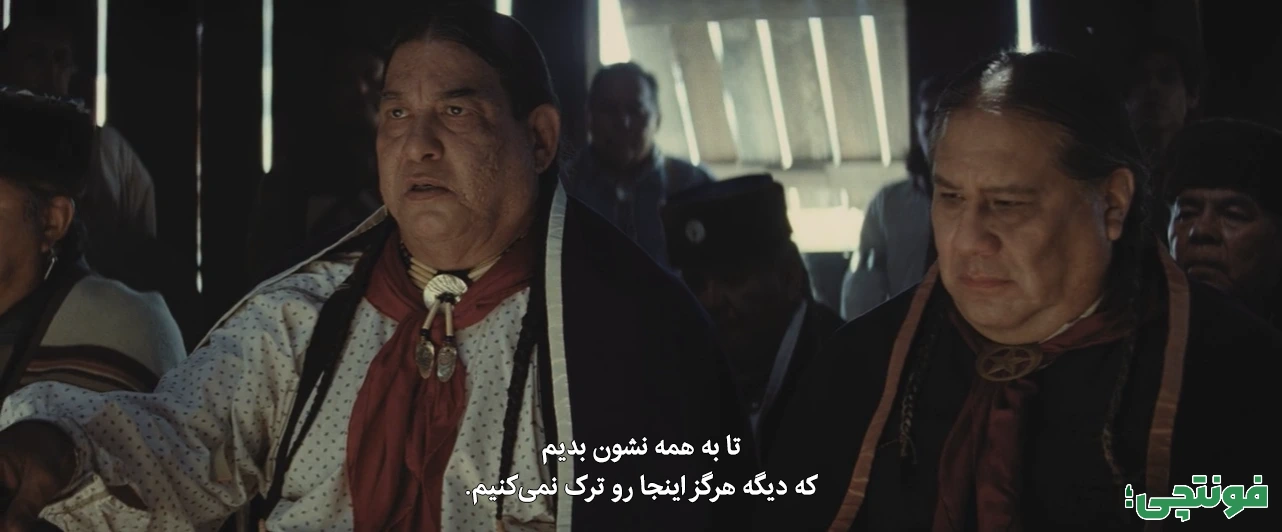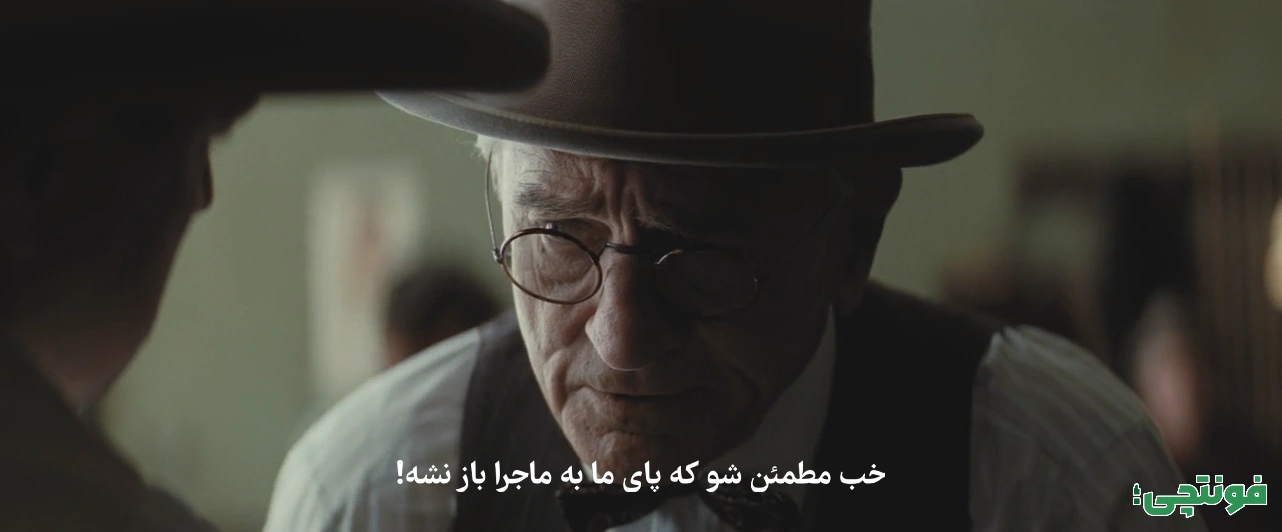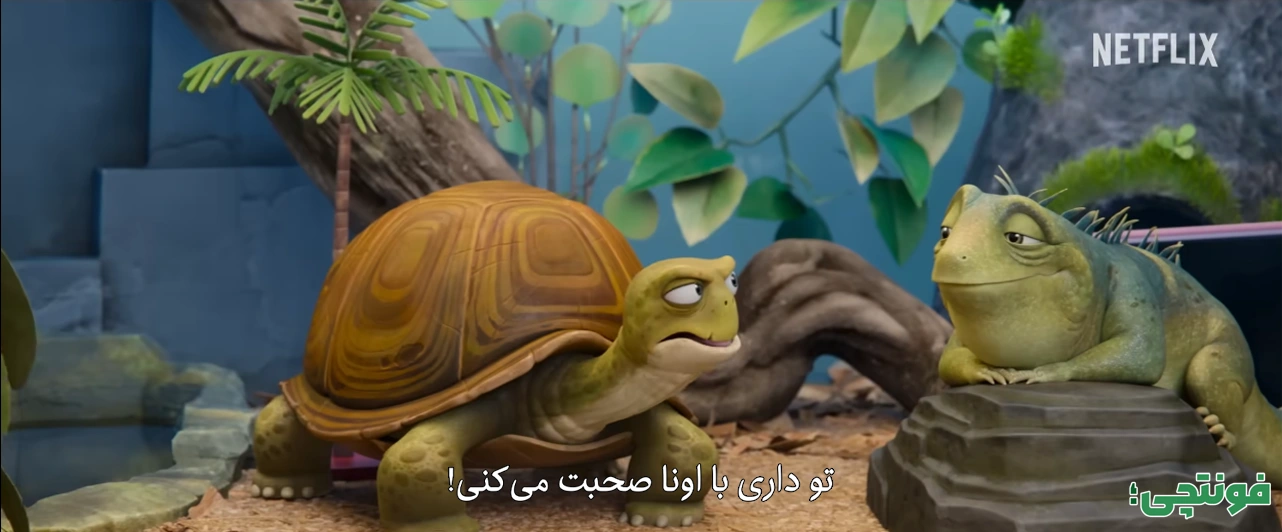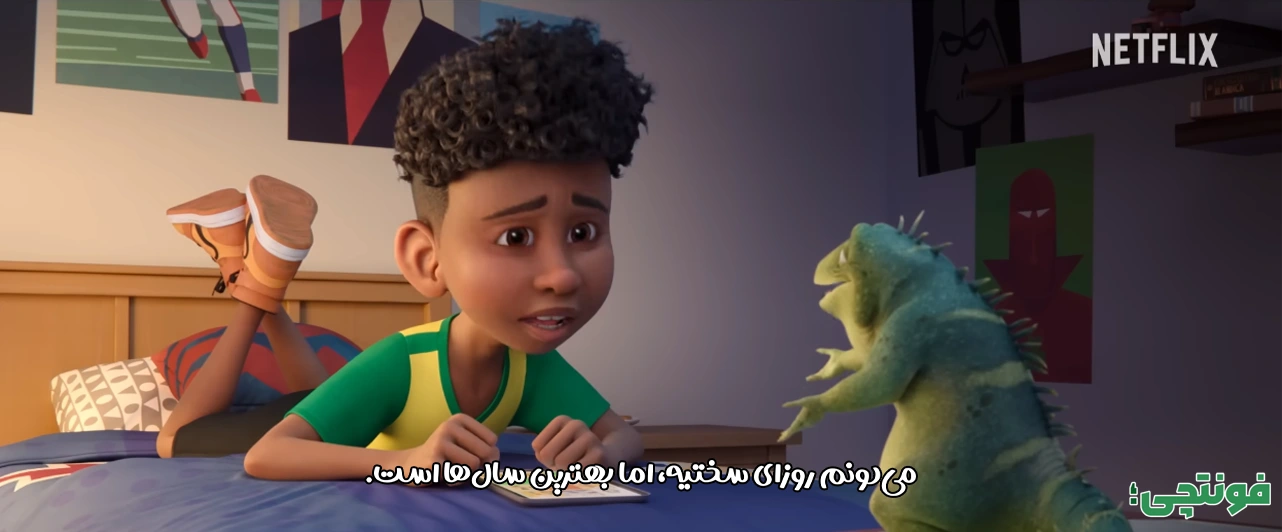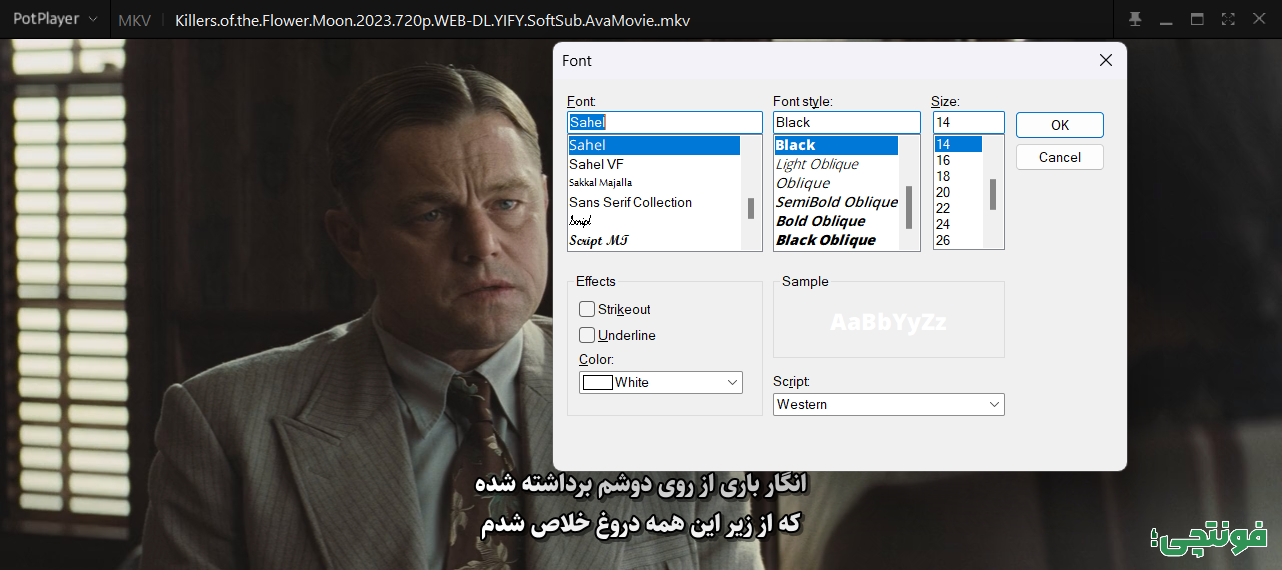
بهترین فونت زیرنویس فیلم و سریال [10+ فونت محبوب]
احتمال میدهم شما هم جزو معدود افرادی هستید که دیدن فیلم و سریال با زبان اصلی را ترجیح میدهند. خصوصا در شرایطی که شاهد تغییر کلی خط داستانی برخی فیلمهای دوبله شده هستیم. مسئله مهمی که شاید خیلیها به آن توجه نکنند زیرنویس فیلم است. انتخاب بهترین فونت زیرنویس فیلم و سریال یکی از راههایی است که میتواند به افزایش لذت دیدن فیلمهای دوبله نشده کمک کند.
وقتی از خیلی افراد علاقهمند به فیلمهای دوبله شده میپرسم چرا فیلم با زبان اصلی نمیبینید؟ پاسخ آنها عموما این است که احساس راحتی ندارند از اینکه صحنه را دنبال کنند یا اینکه به دنبال کلمات زیرنویس باشند. در حالی که اگر روی انتخاب فونت مناسب زیرنویس، تغییر اندازه و حتی جایگاه نمایش آن کمی وقت بگذارند این مشکلات نیز برایشان رفع خواهد شد.
در ادامه این نوشته از وبلاگ فونتچی به بررسی چندتا از بهترین فونت زیرنویس فارسی برای فیلم، سریال و انیمیشن خواهم پرداخت که با استفاده از آنها میتوانید تجربه لذتبخشی در دیدن فیلم، که یکی از محبوبترین سرگرمیهای دنیای امروز است داشته باشید.
بهترین فونت زیرنویس فیلم و سریال
پیش از معرفی فونتهای مناسب زیرنویس لازم است که به چند نکته توجه داشته باشید:
- فونتهای معرفی شده در این نوشته بر اساس ساختار آنها از نظر طراحی و ظاهر قلم دستهبندی شدهاند.
- مسلما این لیست محدود به این موارد نبوده و دهها فونت مناسب دیگر هم وجود دارد.
- مهمتر از همه اینکه، در انتخاب فونت برای زیرنویس فیلم، راحتی بیننده از هر لحاظ اهمیت دارد. پس اگر با فونتهای معرفی شده به هر دلیل احساس راحتی برقرار نمیکنید، بهتر است که سایر فونتها را تست کنید تا چیزی که واقعا با شرایط شما ایدهآل است را انتخاب کنید.
خطر اسپویل: پیش از اینکه ادامه این مطلب را مطالعه کنید، تصاویر این نوشته همراه با فونت زیرنویس فیلم Killers of the Flower Moon 2023 و انیمیشن LEO 2023 تهیه شده است.
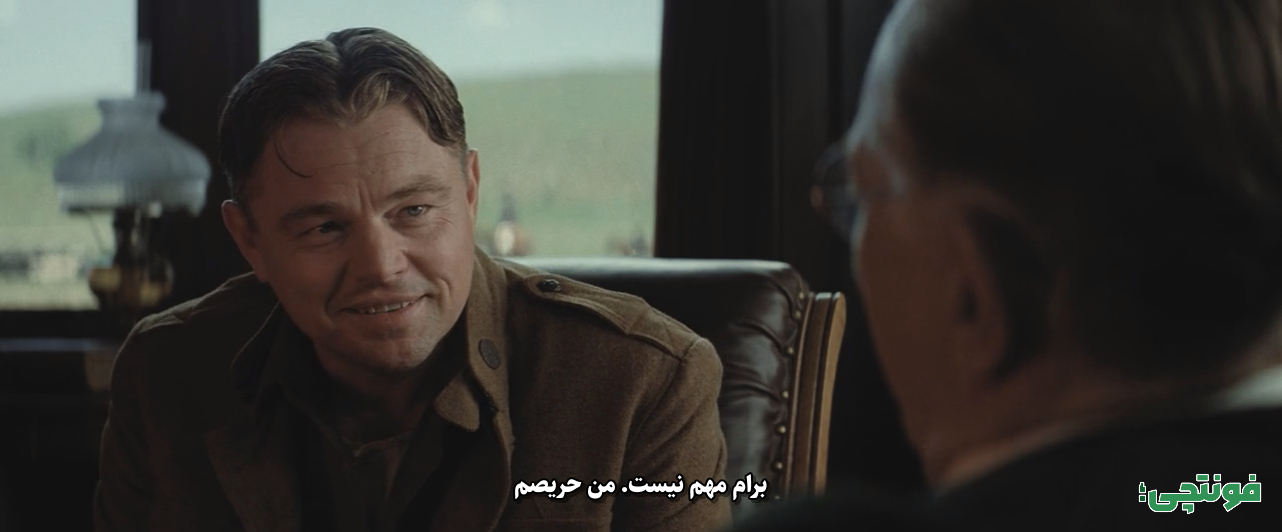
فونت ساحل
فونت ساحل از ساختههای مرحوم صابر راستی کردار است که شخصا بیشترین راحتی را در استفاده از این قلم برای زیرنویس فیلم دارم. مخصوصا در نسخههای ضخیمتر همچون Black که برای نمایشگرهای بزرگتر از ۲۰ اینچ واقعا کاربردی است.
طراحی حروف و کلمات در این فونت بهترین میزان خوانایی را دارد. با اینکه در نگاه اول بیشتر برای عناوین مناسب به نظر میرسد؛ اما در ساختار متن بهخوبی قابل خواندن است. خصوصا برای زیرنویس که سرعت خواندن آن به منظور از دست ندادن صحنهها و همچنین زاویه دید بهتر خود را نشان خواهد داد.
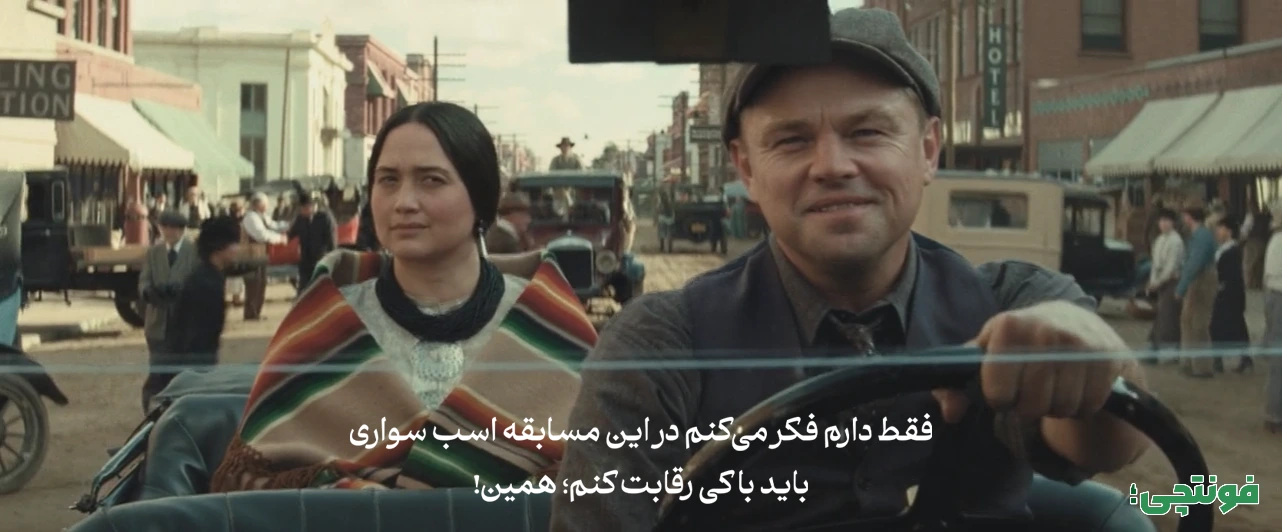
فونت گرامافون برای فیلم تاریخی
بسیاری از افراد به فیلمهای تاریخی علاقه دارند. خودم که شخصا در بین فیلمهای تاریخی به آنهایی که در گروه بیوگرافی بوده و عمدتا بر اساس واقعیت نیز ساخته شده باشند علاقه جدی داشته و دنبال میکنم. پس چه بهتر از قلمی استفاده کنیم که همان حس و حال تاریخی را به بیننده انتقال دهد.
گرامافون یک فونت مناسب زیرنویس فیلم تاریخی است که خود نیز همین سبک تاریخی و نوستالژی گونه را در طراحی حروف دارد. این فونت مجهز به طره هایی در برخی حروف «الف، ک، گ، ل، ط، ظ» است که وجود همین طرهها میتواند در نگاه غیرمستقیم به زیرنویس، خوانش متن و دنبال کردن آن را تا حدی بهبود دهد.
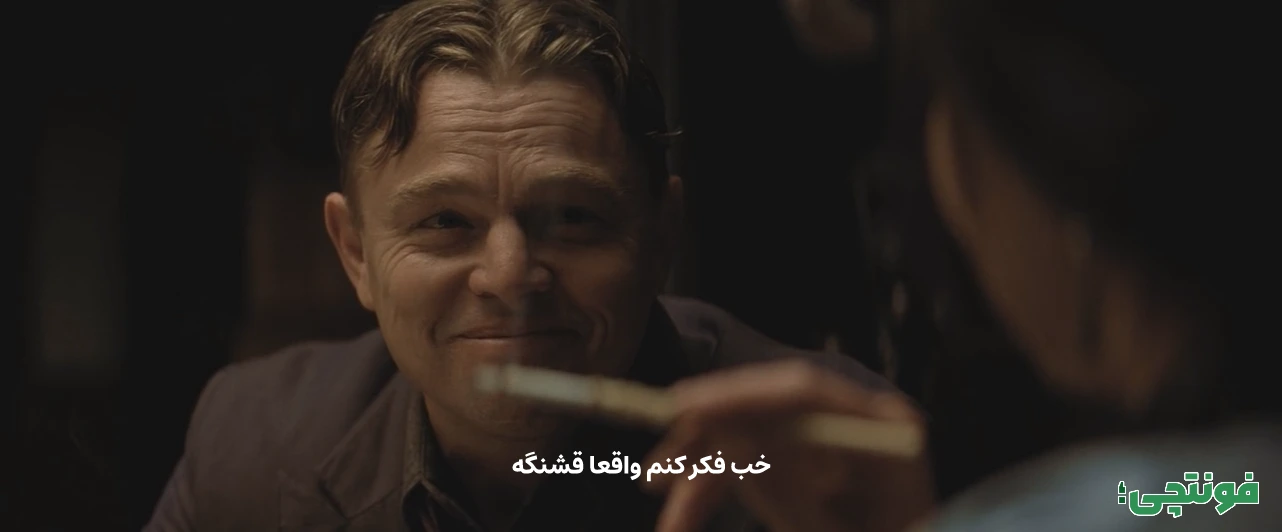
فونت استعداد
اگر به دنبال بهترین فونت زیرنویس رایگان هستید، استعداد یکی دیگر از گزینههایی است که به سادگی نمیتوان از کنارش عبور کرد. این فونت که از نسخه وریبل و پشتیبانی از چند زبان مختلف طراحی شده است، سبک خاصی را در برخی حروف دارد.
در فونت استعداد گردی حروفی همچون «ی، ن، ل» و ساختار متفاوت برخی حروف دیگر که شاید در تضاد با ساختار کلی فونت بهنظر برسد، شکل خاصی را به کلمات خواهد داد که گویی کلمات با ایجاد تضادهایی دستهبندی شده تا سرعت خوانش متن را بالا ببرد.
ویژگی مثبت این فونت برای زیرنویس همین مسائل است. خصوصا اگر از نمایشگر بزرگ برای دیدن فیلم زیرنویس استفاده کنید، وزنهای Bold و احتمالا ضخیمتر Black میتواند سرعت خواندن متن را بالاتر برده و هماهنگسازی بین زیرنویس و دیدن صحنه ها را در حد بالایی حفظ نماید.
فونت ایران سنس X برای زیرنویس
از دیگر فونت های مناسب زیرنویس فارسی ایران سنس است که جزو بهترین فونت های فارسی برای وب سایت است. این قلم نیز از چندین وزن مختلف با امکانات متعدد همچون سبک نقطه گذاری پشتیبانی میکند که اگر مایل به استفاده از نقاط پیوسته باشید انتخاب خوبی خواهد بود.
جدای از همه ویژگیهای مثبت این فونت، خوانایی این قلم به شدت بالاست. به طوری که محدود به زیرنویس فیلم نبوده و در محیطهای مختلف میتواند بهترین عملکرد را از خود به نمایش بگذارد.
گردی حروف و گوشهها در این فونت که برگرفته از خط سنس هستند کاملا نرم بوده و ساختاری دوستانه را به بیننده القا خواهد کرد. دندانهها، چشمیها و دیگر بخشهای حروف نیز طوری طراحی شده که هنگام خواندن زیرنویس در نمایشگرهای کوچک موبایل گرفته تا نمایشگرهای بالای ۳۰ اینچ بهترین عملکرد را از نظر خوانایی دارد.
فونت وزیرمتن
اگر به دنبال فونت رایگان زیرنویس برای فیلم و سریال هستید، تایپفیس وزیرمتن که از دیگر فونتهای مرحوم صابر راستی کردار است، میتواند یک انتخاب بسیار عالی باشد. این قلم مناسب متن است و از چندین وزن مختلف نیز پشتیبانی میکند. ضمن اینکه یک فونت وریبل است که اگر پلیر امکان تغییر وزن را داشته باشد، میتوانید صرفا با نصب یک فایل فونت تمامی وزنها را در اختیار داشته باشید.
خوانایی فونت وزیرمتن نیز مشابه با سایر فونتهای معرفی شده بالا است. اژهها در فاصله مناسبی از هم قرار داشته و برای فیلمهایی که سرشار از دیالوگ بوده و زیرنویسها عموما دو خطی باشند، ساختار فشرده این قلم در اینجا بهتر خود را نشان میدهد.
جمع بندی و کلام آخر